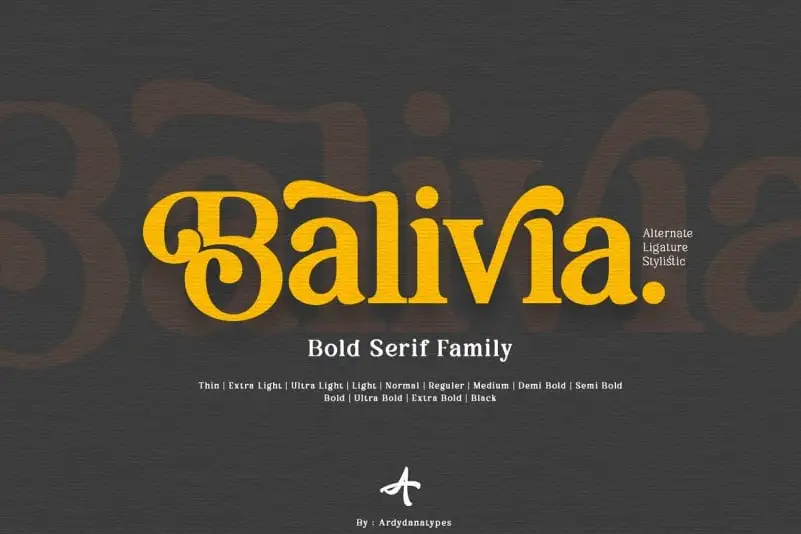
Balivia Serif Font – Fonte Grátis
Balivia Serif Font
A Balivia Serif Font é uma escolha incrível para designers que buscam um estilo clássico contemporâneo. Desenvolvida por Ardyanatypes na plataforma 99designs, esta fonte serif oferece elegância e modernidade ao mesmo tempo, com suas curvas suaves e ligaduras encantadoras. Ela vem em uma ampla variedade de pesos, desde fino até grosso, o que permite inúmeras opções para personalização em diferentes necessidades de design. Independentemente do uso específico de seu projeto, a Balivia Serif traz um toque único, proporcionando uma impressão elegante e moderna. Engajue-se na descoberta desta fonte que certamente enriquecerá seus projetos gráficos.